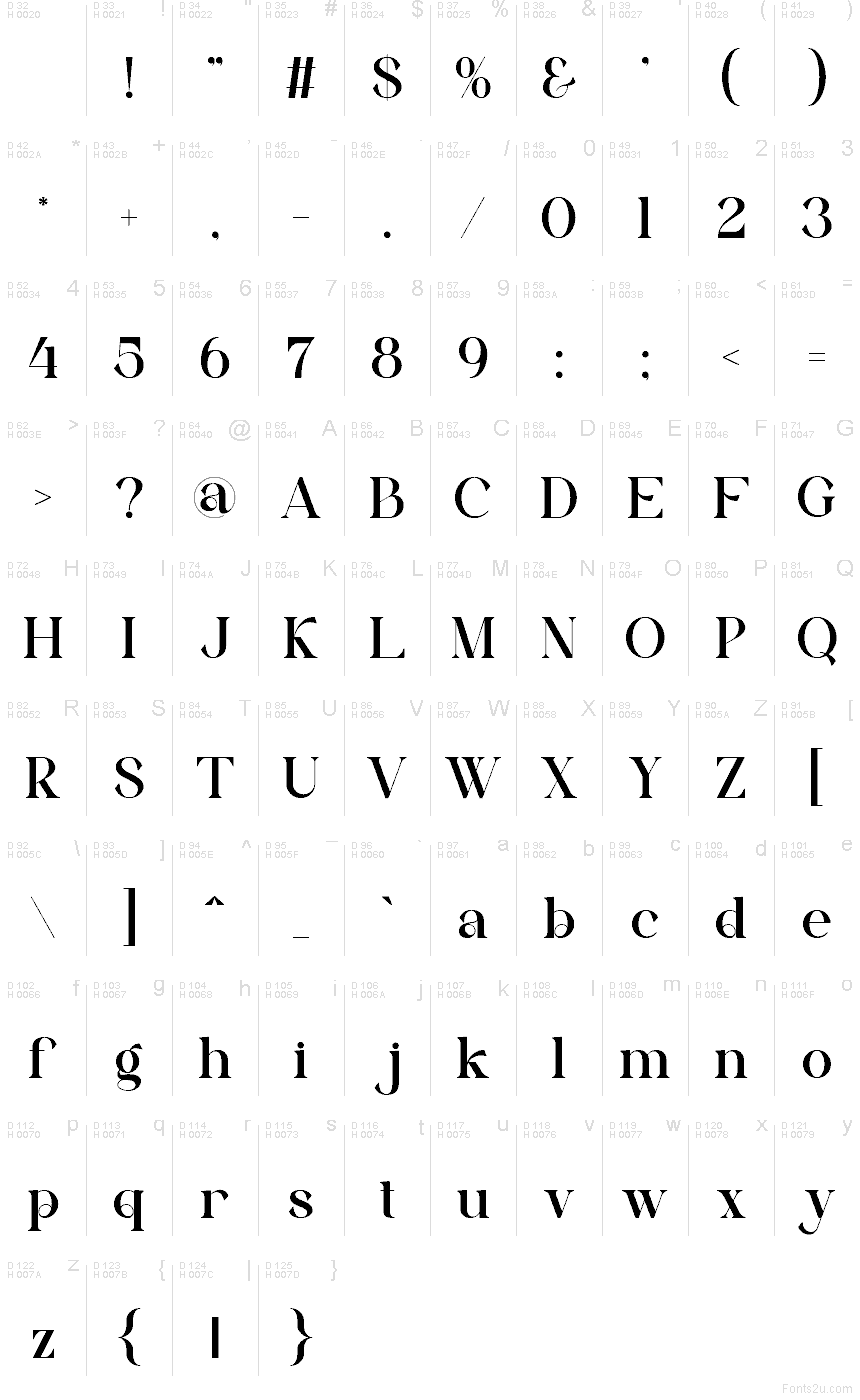
Bikary, bezpłatny, nowoczesny krój szeryfowy typu Didone od Ermedia Studio, łączy dramatyczny kontrast grubych i cienkich linii z delikatnie zaokrąglonymi krzywiznami. Litery sprawiają wrażenie wyważonych i modnych, zestawiając wyraziste, ostre szeryfy z pełnymi, rzeźbiarskimi formami.
Użyj tego darmowego fontu w edytorialach modowych, na opakowaniach kosmetyków, okładkach książek, w nagłówkach kampanii, planszach tytułowych oraz wyrafinowanych monogramach. Wysoko kontrastowy rytm nadaje krótkim słowom elegancki, redakcyjny charakter bez potrzeby stosowania dodatkowych zdobień.